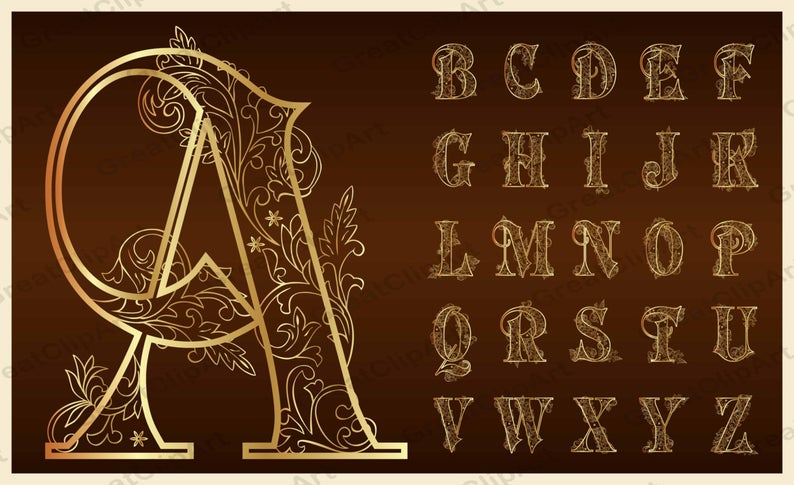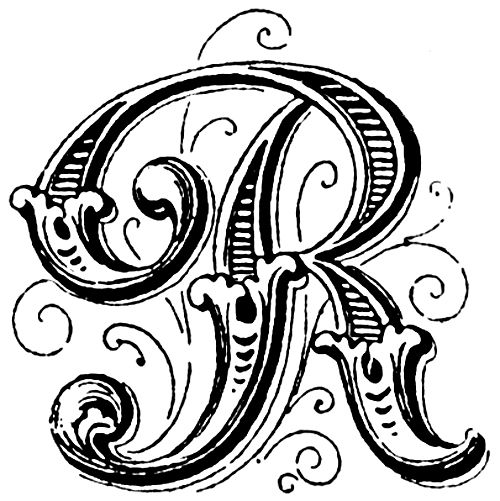
Декоративный шрифт, 4 (четыре) буквы
вязь
Сплетение смежных букв в один сложный знак
«Плетень» из букв
Буквенный орнамент
«плетень» из букв
Буквы, сплетенные в орнамент
Декоративное написание букв
декорат. орнаментальное письмо
Письмо на иконах
декоративное письмо, при котором буквы соединяются в непрерывный орнамент (некоторые виды древнеславянского, арабского письма). Соединение двух или нескольких букв в один составной знак или слитную группу (напр.
, в деванагари).
Декоративное Письмо, При Котором Буквы Соединяются В Непрерывный Орнамент 4 Буквы
ВЯЗЬ
Классификация шрифтов для не-дизайнеров — Sumy Designs
Сегодня дизайнерам доступны миллионы шрифтов.
Большой выбор — это хорошо из-за разнообразия, но плохо, потому что затрудняет выбор идеального шрифта. Может быть, вы ищете определенный шрифт, но не знаете, с чего начать? Может быть, вы просто хотите сообщить своему дизайнеру, какой стиль шрифта вы ищете, но не знаете, как его описать? В любом случае, если вы хотите иметь общее представление об основных стилях, используемых дизайнерами сегодня, вот список для вас. Я собрал общие стили шрифтов, чтобы помочь недизайнерам понять системы типографской классификации в нашем современном мире.
Засечки
Засечки — это маленькие линии или «ножки», выступающие из концов букв. Общее эмпирическое правило заключается в том, что шрифты с засечками легче читать в печатных материалах, потому что засечки выделяют буквы и делают их отличительными, направляя взгляд по странице. Засечки также увеличивают контрастность и интервалы. В наши дни засечки широко распространены в печати и в Интернете.
Sans Serif
Шрифты без засечек — это шрифты, не имеющие выступающих «ножек» в конце строк.